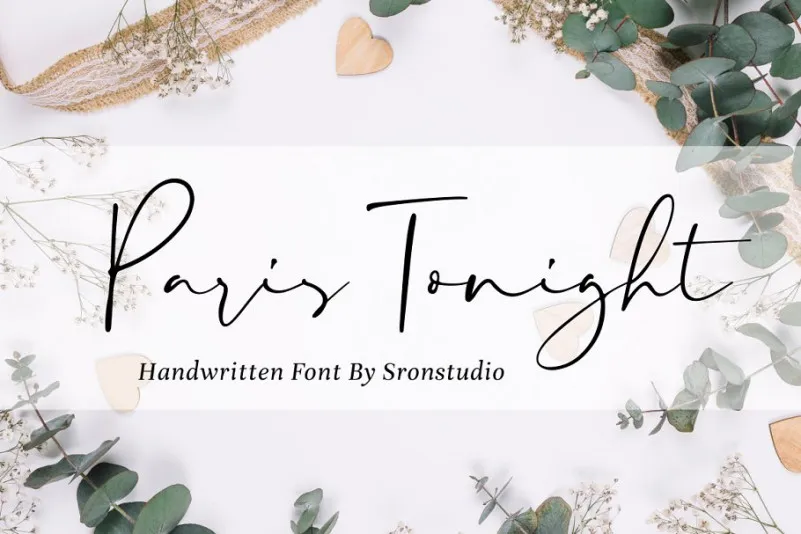
Aqui está uma versão curta e envolvente para a descrição do download desta fonte: Estamos encantados por apresentar à vocês “Paris Tonight Signature Font”, uma fonte de script handwritten criada cuidadosamente. Este design original, desenvolvido pela f0rdesigner, é perfeito tanto para uso em logotipos quanto para invitations e decoração de casamentos. Ideal também para publicações nas redes sociais, embalagens de produtos ou até mesmo como marca d’água para eventos especiais. Feita para atender a uma ampla gama de necessidades, esta fonte é perfeitamente adaptada para criar um estilo único e elegante em seu próximo projeto. Com detalhes refinados e um toque natural na escrita, “Paris Tonight Signature” trará um ar sofisticado às suas criações. Que tal adicionar esse toque autêntico e encantador à sua próxima produção?